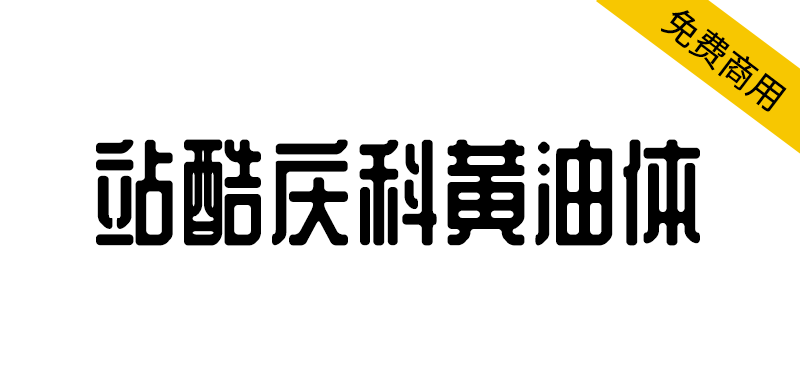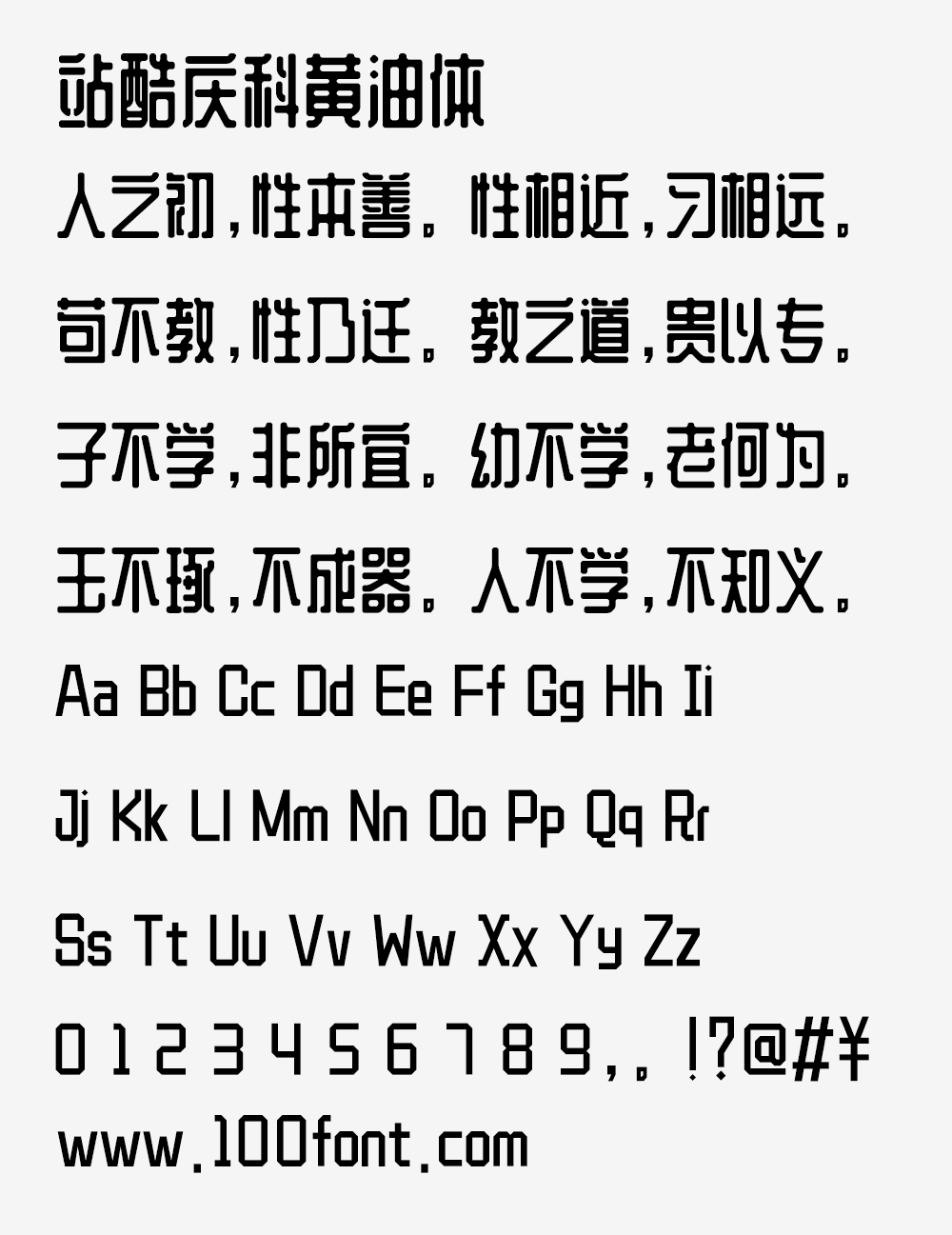
站酷庆科黄油体的设计师为郑庆科,基于中华人民共和国GB2312-80字符集标准,采用TrueType和OpenType两种格式,共收容汉字9181个,英文及标点等常用字符814个。
站酷庆科黄油体是一款字型创新、线条圆润的字体。笔划的每一个直角,都被处理成了半径为4pt的圆角。在设计中需遵循笔划简化但不省略,笔划角度尽量为垂直角度。字体部首的右下角均为45°缺角,提高了字体视觉中心,并有效的解决了一些字体因笔划交叉,字体阅读困难的毛病。